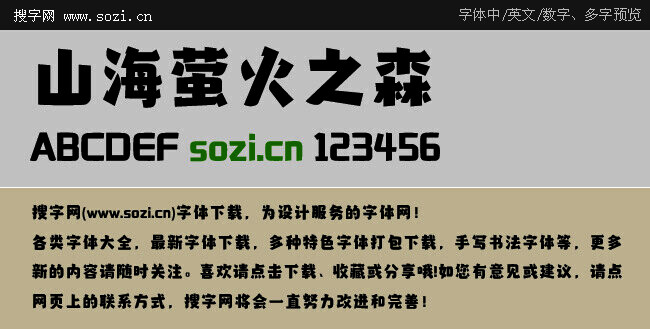
山海螢火之森
搜字網(wǎng)提供一款山海螢火之森中文藝術(shù)字體下載,山海螢火之森是一款卡通風(fēng)字體,包含簡體漢字6763個。字體童趣可愛,結(jié)構(gòu)多變靈動,字形活潑清新,造型生動有趣,具有靈活的適用性,天真俏皮又不失時尚感。適合兒童包裝設(shè)計、卡通海報設(shè)計、廣告設(shè)計等應(yīng)用。